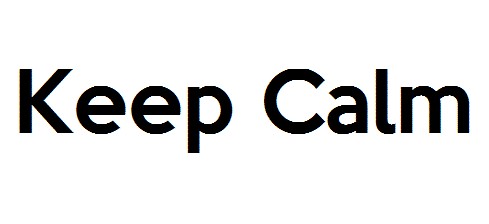
keep calm medium ttf字體效果偏粗,適用于正文當(dāng)中的英文字體,面對市面上如此繁瑣的英語字體,不同樣式的字體都有著其獨(dú)有的豐富,這款字體在常見的樣式上又多了些許藝術(shù)設(shè)計(jì),需要的用戶可以來下載試用。
keep calm是一款工整大方的英文字體,該字體工整、規(guī)范,可以廣泛地應(yīng)用于各類廣告設(shè)計(jì)、PPT設(shè)計(jì)、海報(bào)制作、影視設(shè)計(jì)以及網(wǎng)頁設(shè)計(jì)等領(lǐng)域。
找了這個字體很久了,很漂亮的字體,特別的工整簡潔,看起來很舒服!